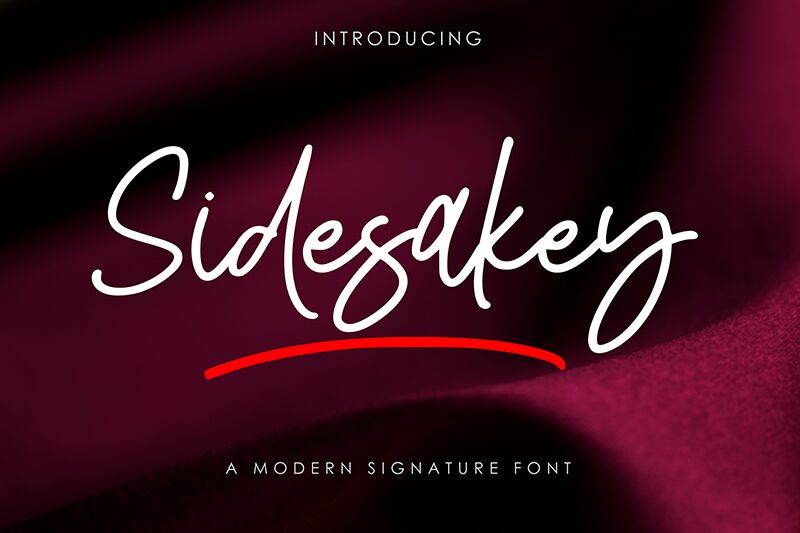
Sidesakey от AMINMARIO — это бесплатный рукописный шрифт с непринужденным, индивидуальным ритмом и слегка элегантным наклоном. Буквы выглядят нарисованными одним уверенным движением, сочетая длинные размашистые кривые с узкими соединениями и несколькими высокими штрихами, которые придают словам воздушность, напоминающую росчерк пера.
Он идеально подходит для брендинга, упаковки бутиков, цитат в социальных сетях, заголовков приглашений, а также для обложек в стиле beauty или lifestyle, где требуется бесплатный шрифт, выглядящий легко, но при этом гармонично. Используйте его для коротких заголовков, эскизов логотипов или инициалов: удлиненные кривые и восходящие штрихи придают словам динамику.